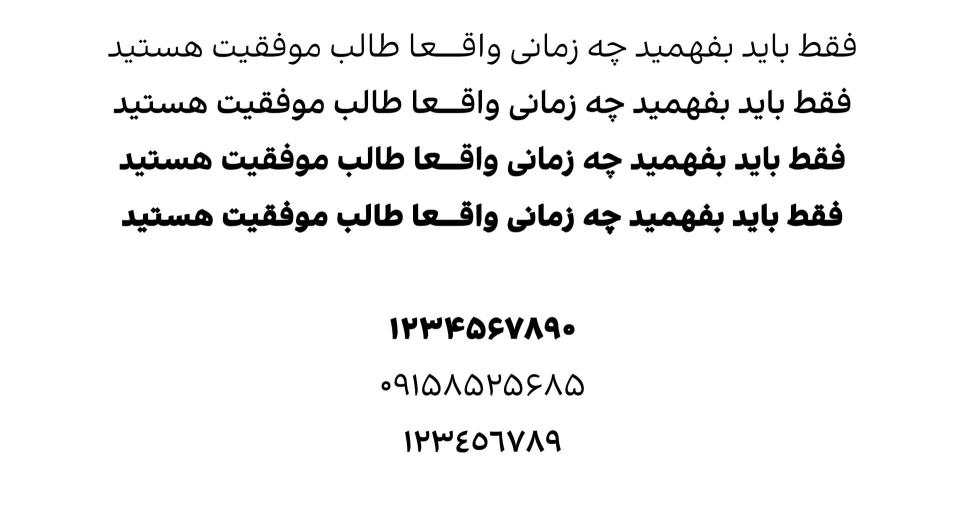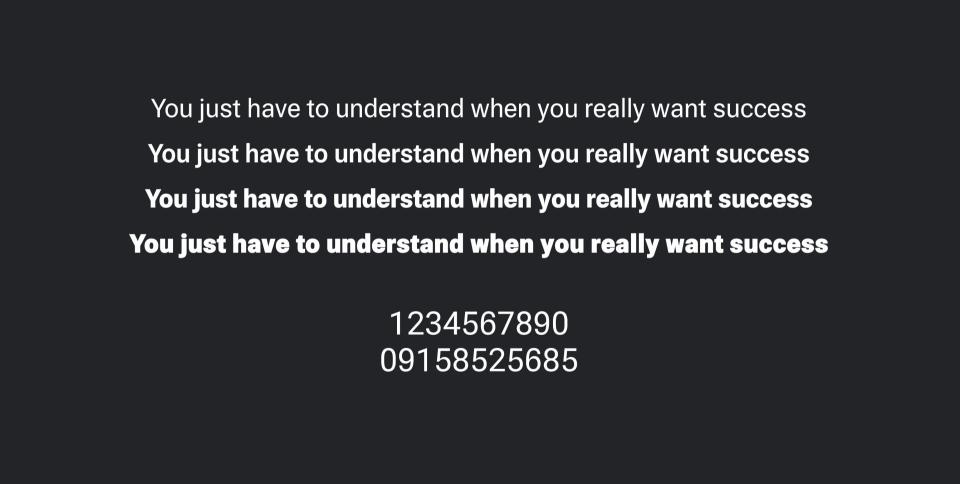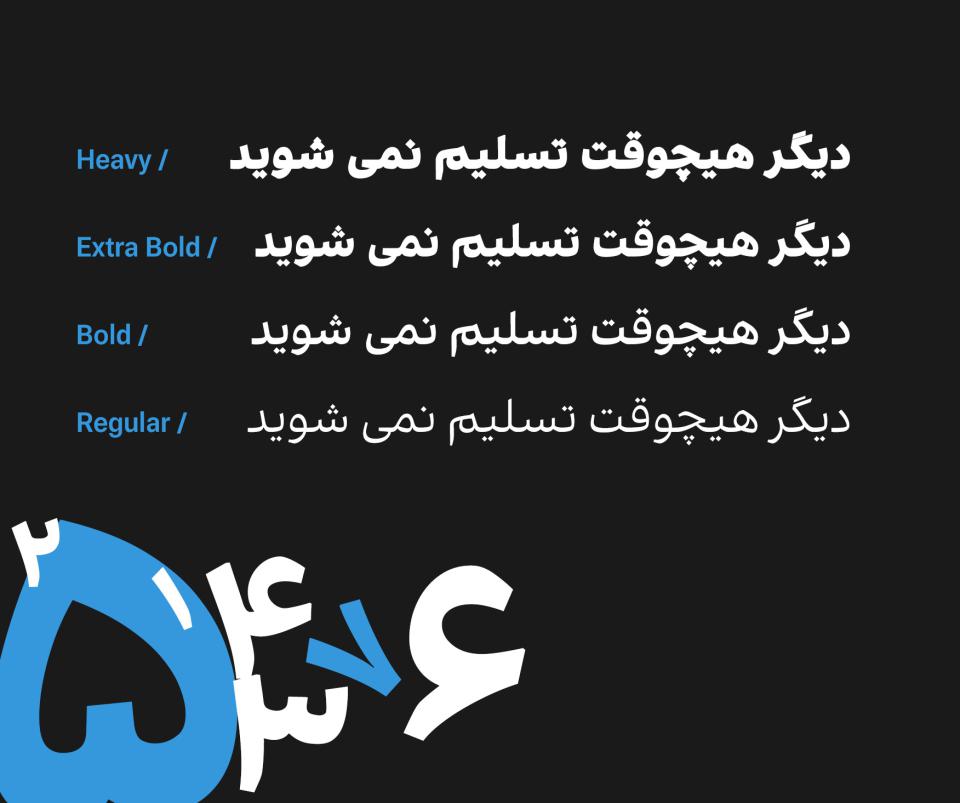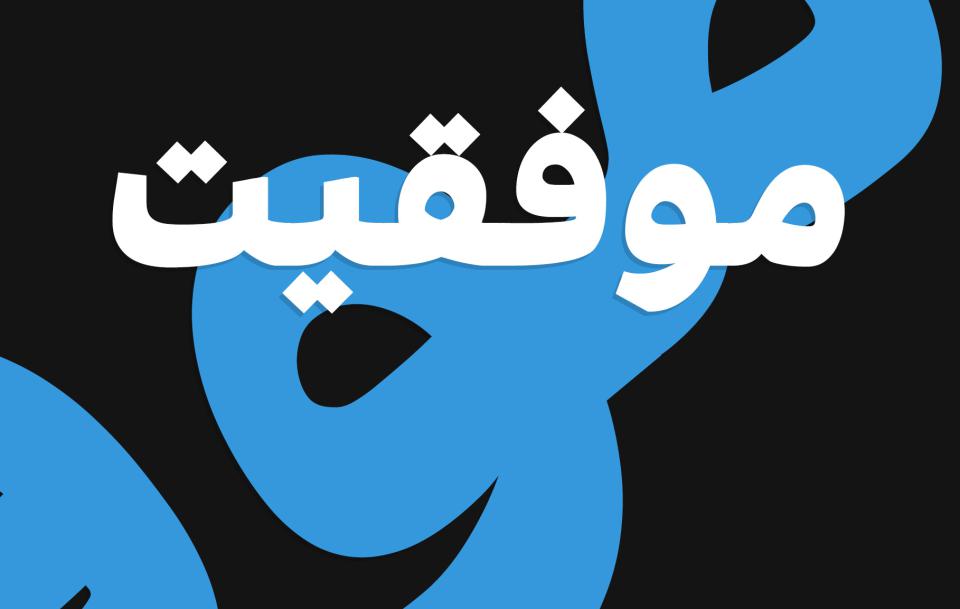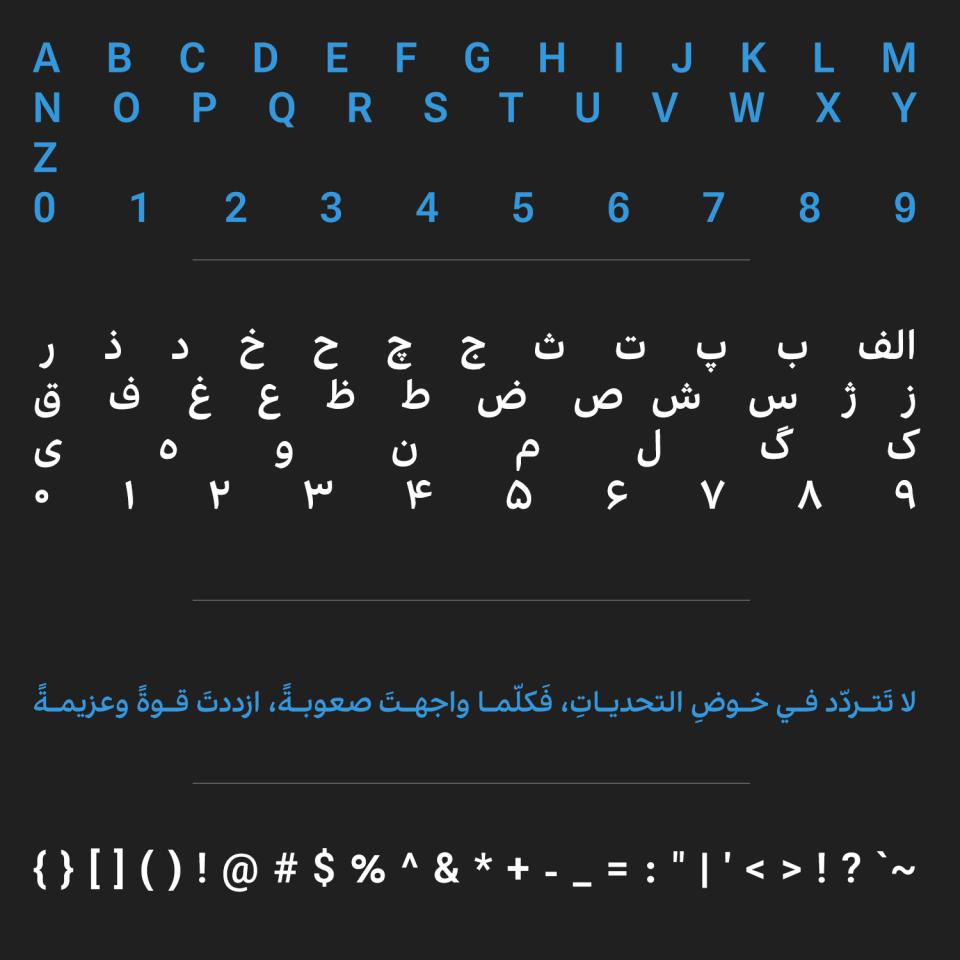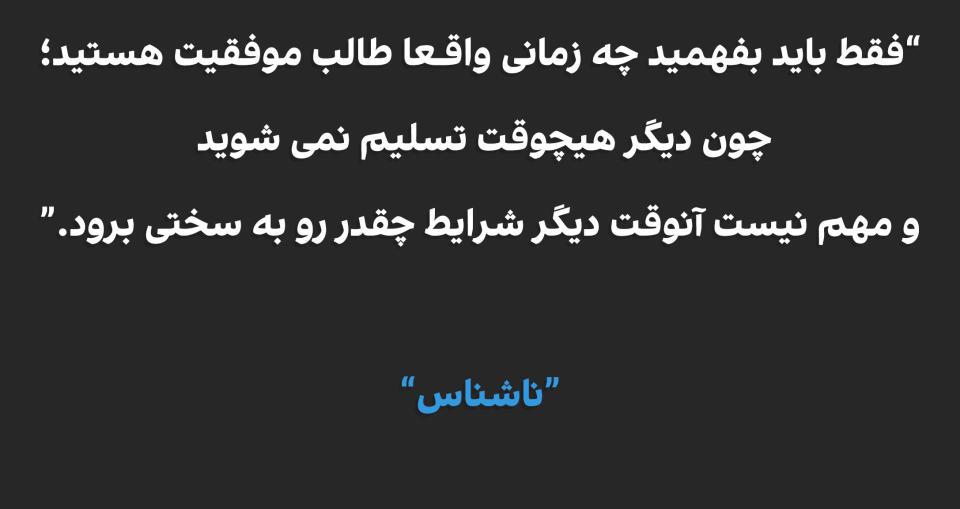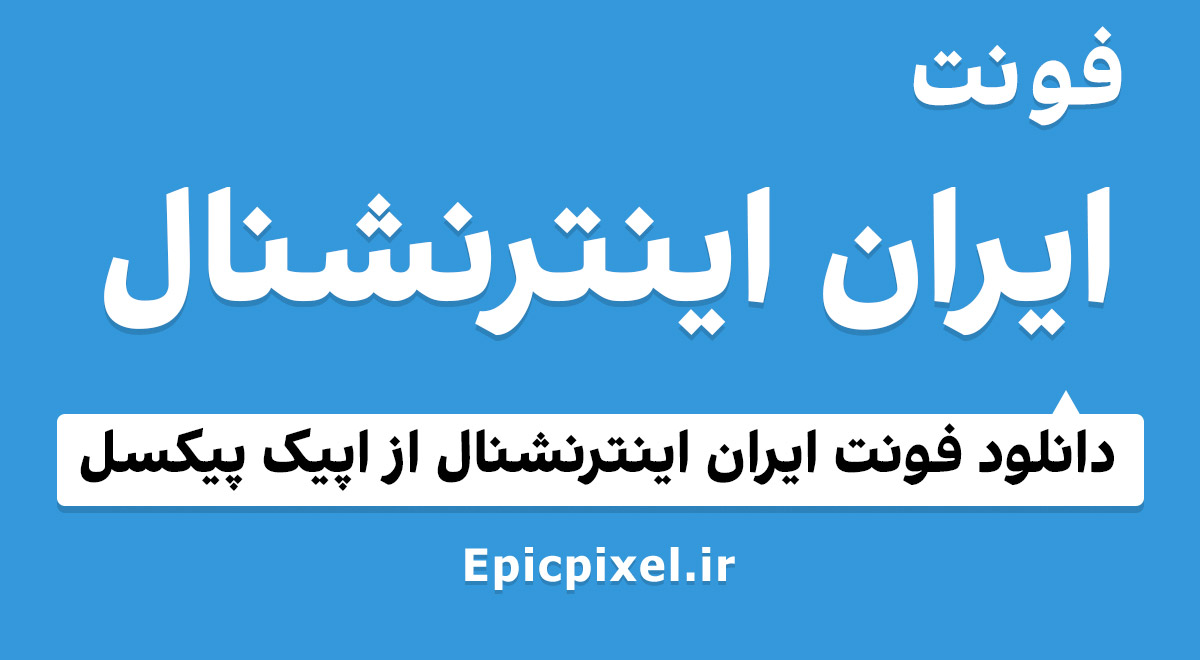
4 فونت ایران اینترنشنال فارسی
| ⭐ توضیحات | آیا میخواهید وبسایت یا مقاله ، طراحی خبری خود را حرفهایتر کنید و اعتماد مخاطبان را جلب نمایید؟ فونت ایران اینترنشنال با خوانایی بالا، طراحی مدرن و پشتیبانی کامل از زبان فارسی، گزینهای ایدهآل برای وبسایت شماست. |
در دنیای شگفت انگیز فونت ایران اینترنشنال غوطه ور شوید
فونت ایران اینترنشنال: فراتر از یک انتخاب ظاهری
در دنیای وب، جزئیات ظریف بسیاری وجود دارد که بر تجربه کاربری و در نهایت، موفقیت یک وبسایت تأثیر میگذارد. انتخاب فونت مناسب، یکی از همین موارد است. فونت ایران اینترنشنال، که به طور خاص برای این شبکه خبری طراحی شده، نقشی کلیدی در انتقال پیام و حرفهای به نظر رسیدن وبسایت آنها ایفا میکند.
اما داستان در همینجا تمام نمیشود. در این مقاله، قصد داریم سفری به دنیای پنهان فونت ایران اینترنشنال داشته باشیم و رمز و رازهای آن را کشف کنیم. بیایید با هم ببینیم که این فونت چه ویژگیهایی دارد و چرا انتخابی ایدهآل برای وبسایتهای خبری به شمار میرود.
ویژگیهای منحصر به فرد فونت ایران اینترنشنال
- خوانایی فوقالعاده: خوانایی بالا، یکی از مهمترین ویژگیهایی است که یک فونت خبری خوب باید داشته باشد. فونت ایران اینترنشنال به گونهای طراحی شده که خواندن حروف در اندازههای بزرگ و تیترها، و هم در اندازههای کوچکتر و متن اصلی، راحت باشد. این ویژگی به مخاطبان شما کمک میکند تا بدون هیچ زحمتی، بر روی محتوای وبسایت تمرکز کنند.
- حرفهای و رسمی: فونت ایران اینترنشنال، با خطوط تمیز و طراحی مدرن، به وبسایت شما ظاهری حرفهای و رسمی میبخشد. این ویژگی برای وبسایتهای خبری که میخواهند اعتبار و اعتماد مخاطبان خود را جلب کنند، بسیار حائز اهمیت است.
- قابل انعطاف: این فونت طیف وسیعی از وزنها را ارائه میدهد که باعث انعطافپذیری آن در طراحی میشود. شما میتوانید با توجه به نیاز خود، از وزنهای مختلف فونت برای ایجاد سلسله مراتب بصری و تفکیک تیترها، زیرعنوانها و متن اصلی استفاده کنید.
- پشتیبانی از الفبای فارسی: فونت ایران اینترنشنال به طور کامل از الفبای فارسی پشتیبانی میکند و تمامی حروف و علائم نگارش زبان فارسی را به درستی نمایش میدهد. این ویژگی برای وبسایتهایی که به زبان فارسی فعالیت میکنند، ضروری است.
اگر به دنبال راهی برای حرفهایتر کردن وبسایت خبری خود و جلب اعتماد مخاطبان هستید، فونت ایران اینترنشنال انتخابی ایدهآل برای شماست. این فونت با خوانایی بالا، طراحی حرفهای، انعطافپذیری و پشتیبانی کامل از زبان فارسی، تجربهای کاربری عالی برای مخاطبان شما رقم خواهد زد.